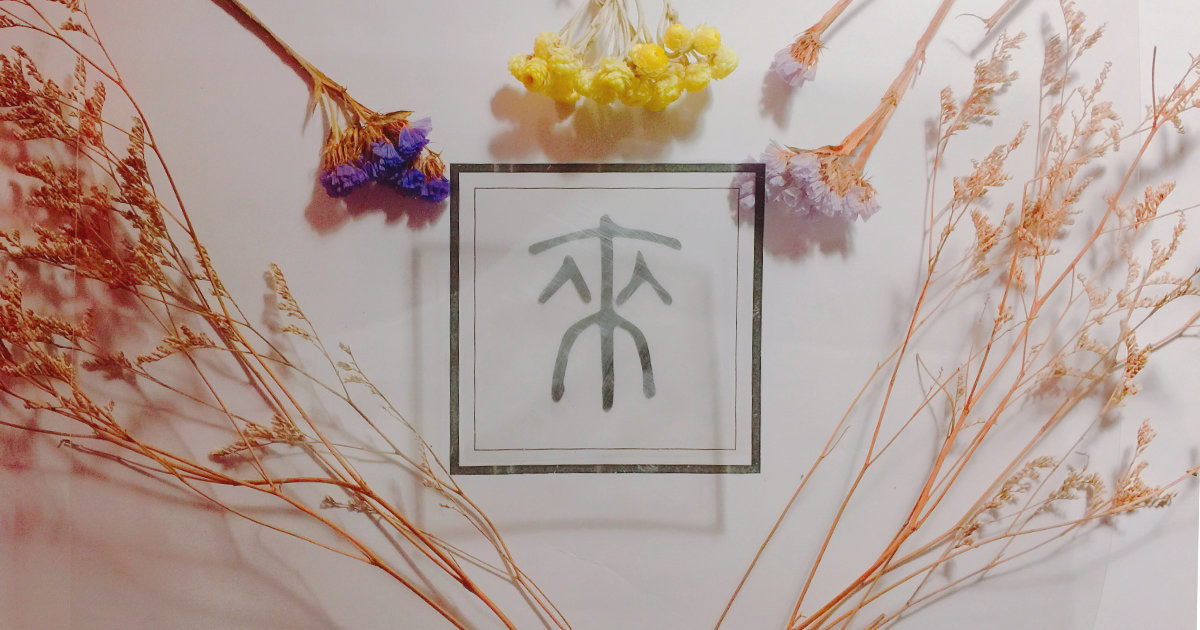
以剛克剛,來互相傷害啊!
這麽做
就能將你的名字
造成接近永恆的樣子
篆刻是浪漫的。對於文字工作者 aka 字型設計師來說,同樣是在白色的空間佈局,求取平衡。我們或許能夠從這項古老記憶學到新的觀念。尤其,脫離了熟悉的書寫、向量繪圖,遇到要與真實材質與共舞的場合,文字設計又會怎樣變化呢?本著這樣的好奇心,我們願與各位一同踏入篆刻初學者的世界。